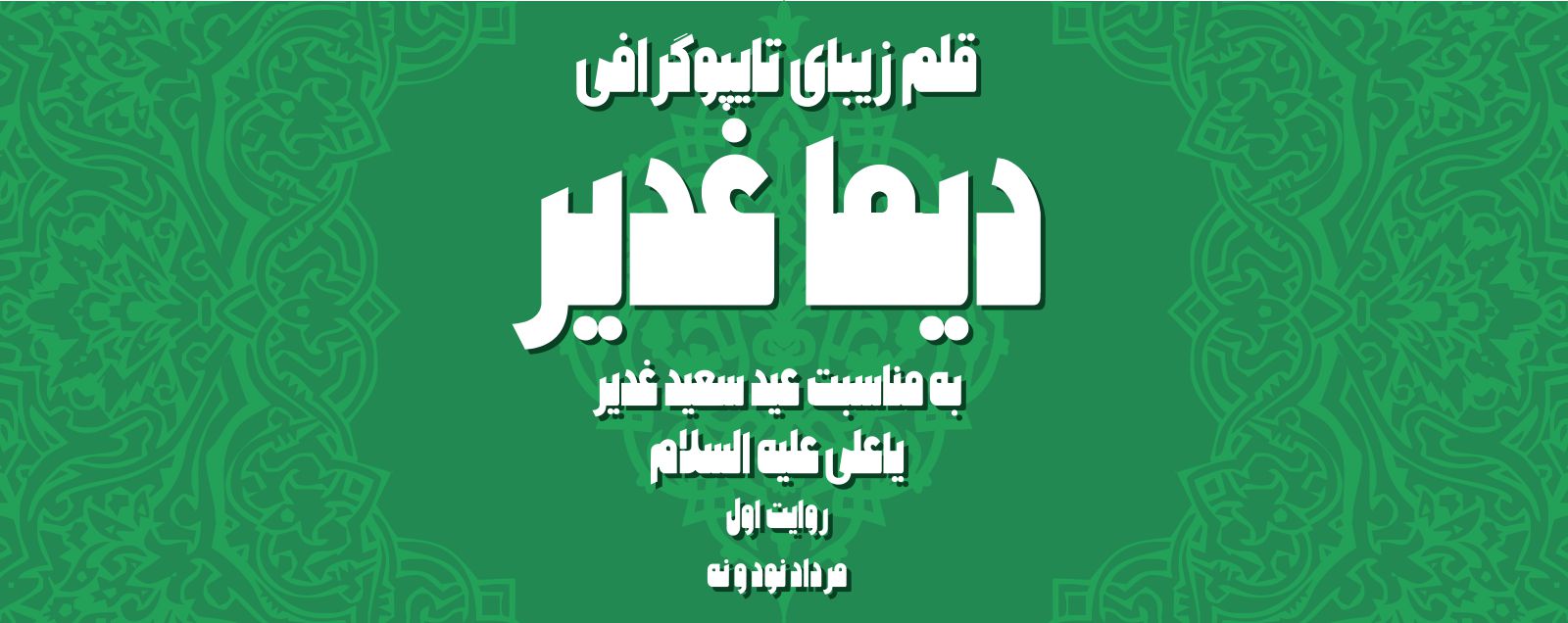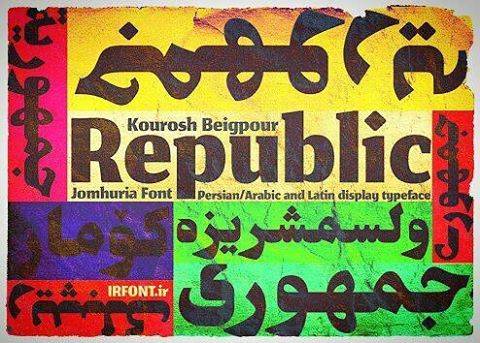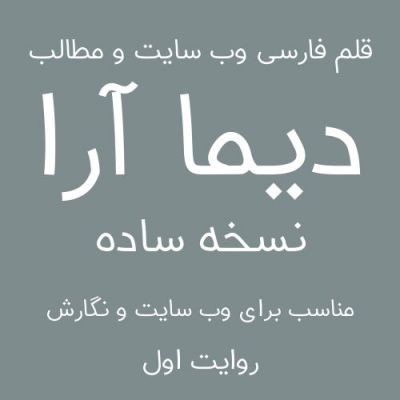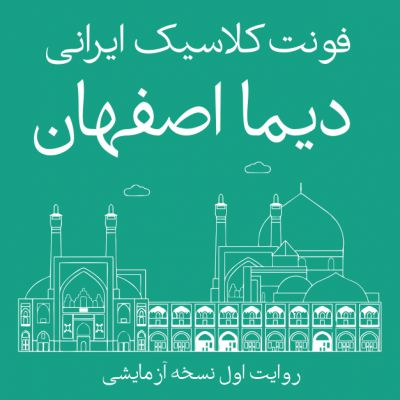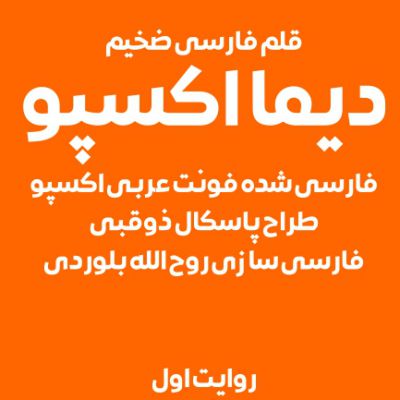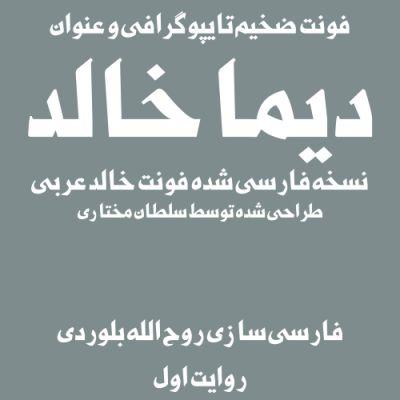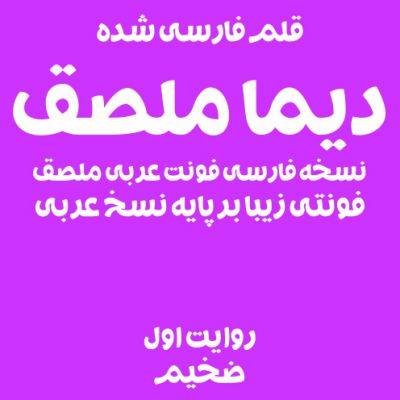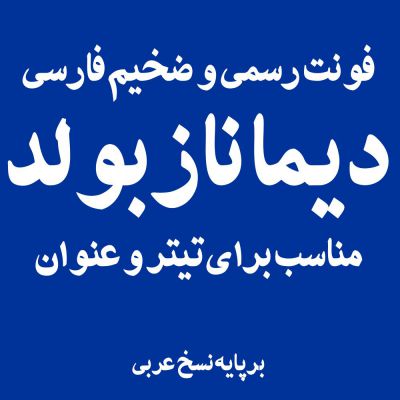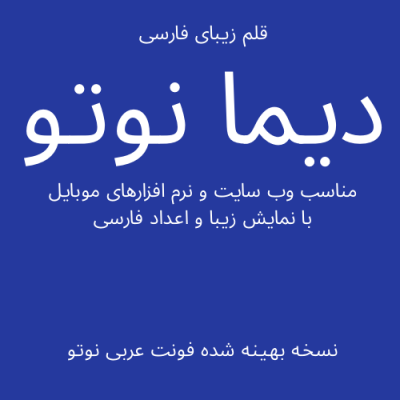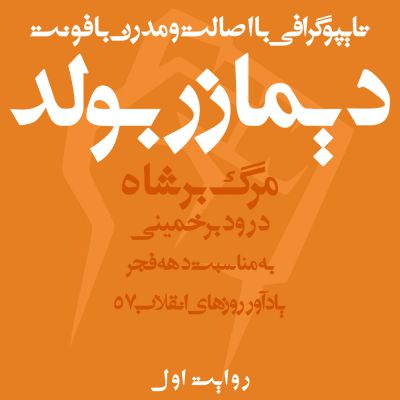
برای امروز سری کامل خانواده فونت لئونس یا لئونکست را آماده کردیم. این سری فونت 14 وزن متفاوت دارد. از این فونت برای هر موقعیتی می توان اس...
فونت جمهوری یک فونت درشت و مناسب برای تیتر و عناوین می باشد. طراح قلم کوروش بیگ پور می باشد....
قلم رایگان تهران یک قلم زیباست که فونت های مشابه اون مثل حماسه نیز تولید شده متاسفانه نام طراح فونت رو پیدا نکردیم اما نسخه اصلاح شده هاک...
این قلم یک قلم کلاسیک براساس خط نسخه عربی می باشد....
این قلم توسط طراح کرد نزار طراحی شده است. فونتی زیبا و در دو وزن متفاوت و رایگان...
این قلم توسط شرکت اینتل و برای استفاده رایگان منتشر شده است. فعلا فقط دو وزن از این قلم در دسترس می باشد....
این قلم نسخه بتا می باشد و هنوز در حال تکمیل است. پس اگر مشکلی دیدید در قسمت نظرات انرا منعکس کنید. این فونت برای وب سایت ها طراحی شده اس...
قلم دیما پلاتین یا پلاتینیوم (طلای سفید ) نسخه ضخیم در وزن 800 دومین نسخه از سری فونت زیبا دیما پلاتین با کاربرد وب سایت و موبایل است. ای...
فونت مرکزی از فونت های رایگان سرویس گوگل می باشد که توسط طراح ایرانی برنا ایزد پناه طراحی شده است. این فونت مناسب استفاده در وب می باشد....
قلم دیما پلاتین یا پلاتینیوم (طلای سفید ) نسخه لایت در وزن 300 اولین نسخه از سری فونت زیبا دیما پلاتین با کاربرد وب سایت و موبایل است. ای...
فونت بهیج پالاتینو عربی از سری فونتهای تصحیح شده ایست که توسط یک آکادمی مجازی توسعه یافته است. این فونتها تصحیح شده ی فونتهای رایج فارسی،...
فونت جدید دیما زر نازک برای طراحی و استفاده در موبایل یا سایت یا نرم افزارهاییی که نیاز به فونت بسیار نازک دارند کاربرد دارد. این فونت از...
قلم دیما غدیر به مناسب عید غدیر خم و ولایت حضرت علی علیه السلام بصورت رایگان منتشر شد.! التماس دعا ﺭﻭﺯﯼ ﺳﻠﻄﺎﻥ محمدﺧﺪﺍ ﺑﻨﺪﻩ ﺗﺼﻤﯿﻢ ...
فونت کارا توسط شرکت همکاران سیستم به صورت رایگان منتشر شده فونت مدرن و زیبایی است که با خوانایی مناسب میتواند برای متون طولانی در نشر رو...
این قلم کامل ترین قلم عربی فارسی کردی و اردویی است که تا کنون با ان برخورد کرده اید. تعداد زیاد حروف جایگزین (الترناتیو) در این فونت مثال...
تایپفیس استعداد مجموعه فونت ۵ وزنی سازگار با وب، طراحی شده برای استفاده در متون بلند و منتشر شده تحت مجوز آزاد است. با تشکر از کمکهای ب...
قلم زیبا ال موهاناد عربی فونتی زیباست که تا کنون نسخه های متفاوت با نام های زیاد از این فونت به عربی و فارسی منتشر شده , فونت ال موهاناد ...
این قلم در بیش از ۵ وزن برای زبان های عربی فارسی انگلیسی و اردو و کردی منتشر شده است. طراحی زیبا بر پایه نسخه از خصوصیات این فونت است....
خیلی وقت بود که دنبال یه فونت مناسب برای اپ های موبایل و وب سایت بودم ٫ بعد از گردش فراوان فونت نوتو که بسیار شبیه فونت ایران سانس می باش...
این فونت یک فونت زیباست که براساس نسخ عربی طراحی شده ٫این فونت زیبا با ویرایش های انجام شده برای طراحی لوگو نام کتاب و پوستر کاملا کاربر...
قلم دیما اکسپو یک فونت ضخیم عربی است که توسط پاسکال ذوقبی طراحی شده و توسط روح الله بلوردی فارسی سازی شده است....
دیما خالد یک فونت فارسی شده براساس فونت عربی خالد بولد می باشد. این فونت ضخیم مناسب طراحی و لوگو و عناوین می باشد....
دیما آرا اولین فونت از تایپ فیس دیما آرا در وزن ساده و برای وب سایت می باشد. این فونت برای توسعه وب سایت های ایرانی در نظر گرفته شده است....
دیما ناز بولد اولین فونت از سری فونت های تایپ فیس ناز بصورت سریف دار برای مجلات و روزنامه ها و وب می باشد که بصورت رایگان منتشر شده است. ...
مرحوم حسین عبد الله زاده حقیقی، طراح فونتهای زر( نازک و سیاه) و تیتر به سفارش ...
این قلم رو خیلی وقت پیش ک...
با سلام خدمت شما دوستان عزیز ُدر شروع سال ۹۷ سومین فونت دیما نیز منتشر شد. این فونت که فونتی کلاسیک برپایه نسخه عربی می باشد که سریف های...
قلم رسمی دیما دیجیتال یک قلم برای استفاده در نرم افزار ها یا در وب سایت هایی است که میخواند نوشته های بسیار ریز را خوانا نشان دهند ، این ...